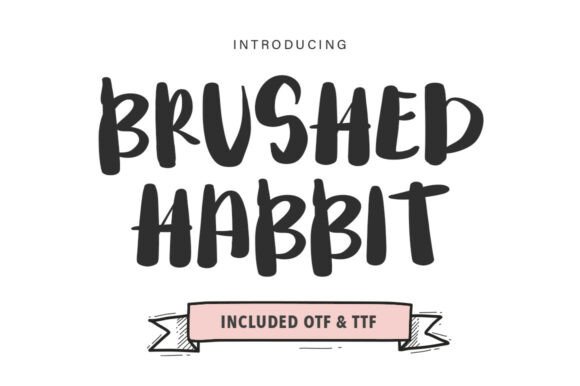
Brushed Habbit
適切なデザイン要素を見つけるのは難しい場合がありますが、Brushed Habbitは作品を即座に引き立てる優れたコレクションを提供します。
POD(オンデマンド印刷)製品、結婚式の招待状、またはソーシャルメディアのグラフィックを作成している場合でも、Brushed Habbitは理想的です。